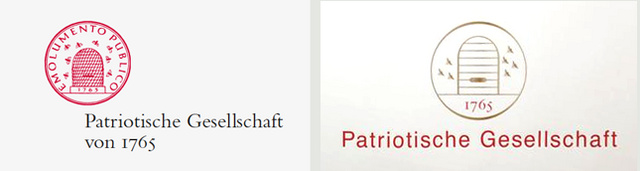
Neues Logo für zivilgesellschaftliche Organisation
Schade. Das alte fand ich wesentlich passender. Allein die viel zu weit gesperrte Helvetica … :neenee: